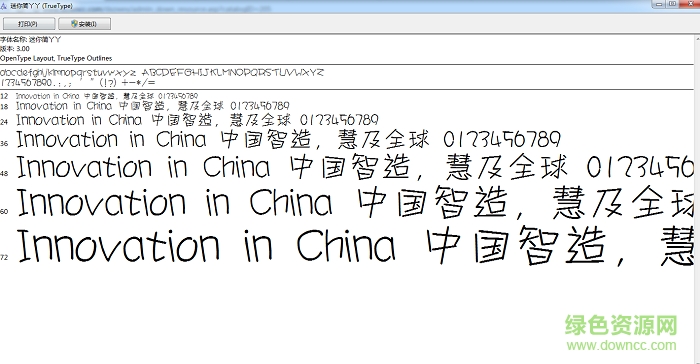
jyaya字體是一款稚嫩的迷你卡通字體,線條逼直,歪歪扭扭雖然不符合標(biāo)準(zhǔn)字形構(gòu)造看起來(lái)卻別具一格,獨(dú)特有趣,使用效果不錯(cuò),非常適合女性用戶(hù)在書(shū)寫(xiě)特殊文章的時(shí)候使用,整體排版效果也非常的亮眼,需要的朋友就來(lái)綠色資源網(wǎng)下載使用吧!
jyaya字體特點(diǎn)
迷你簡(jiǎn)丫丫體筆畫(huà)均為直線,字體結(jié)構(gòu)卻很是獨(dú)特,歪斜有趣,天真爛漫。